Professionelle Satzprogramme wie Adobe InDesign bieten umfangreiche Möglichkeiten, Texte mikrotypografisch zu formatieren und zu bearbeiten. Allerdings lässt sich auch völlig programmunabhängig vieles in digitalen Texten verankern, wenn man die entsprechenden Zeichen kennt und weiß, wie man sie ansprechen kann. Eine Übersicht der wichtigsten Zeichen.
Das geschützte Leerzeichen
Das geschützte Leerzeichen (Unicode U+00A0) kann Umbrüche verhindern, die den Lesefluss stören würden. Dies ist zum Beispiel immer dann der Fall, wenn durch ein Leerzeichen getrennte Teile als eine Einheit betrachtet werden sollen. Beispiele:
15. Jahrhundert
z. B.
Prof. Dr. Müller
50 mm
Gerade in der digitalen Typografie (Websites, E-Books etc.), wo der Textfluss dynamisch ist und nicht vom Autor oder Gestalter einer Textes kontrolliert wird, bietet sich der Einsatz geschützter Leerzeichen an. Und so kann das geschützte Leerzeichen angesprochen bzw. kodiert werden:
Windows: Alt + 0160 (mit den Ziffern auf dem Ziffernblock)
MacOS: Wahltaste + Leertaste (wo unterstützt)
E1-Tastatur: Alt(Gr) + Leertaste
HTML:
Geschützte Leerzeichen (normalbreit und schmal) im Einsatz in InDesign und Word
Auch ein schmales geschütztes Leerzeichen (U+202F), das sich insbesondere für Abkürzungen eignet, ist im Unicode-Standard vorhanden. Da es jedoch im Gegensatz zum regulären geschützten Leerzeichen nicht innerhalb des westeuropäischen 8-Bit-Zeichenvorrates liegt, ist es weniger gut unterstützt.
Windows (in einigen Programmen):
Alt + 8239 (mit den Ziffern auf dem Ziffernblock)
2, 0, 2, F, Alt+C oder 2, 0, 2, F, Alt+X (in Microsoft-Office-Programmen)
MacOS: nicht direkt ansprechbar (Alternativen siehe hier)
E1-Tastatur: Alt(Gr) + c
HTML:
Der bedingte Trennstrich
Der bedingte Trennstrich (U+00AD) erlaubt die Vorgabe sinnvoller Trennfugen in digitalen Texten. Wenn der Trennstrich nicht gebraucht wird, bleibt er unsichtbar und wirkt sich auch nicht negativ auf eine Verarbeitung der Texte (z. B. durch Suchmaschinen), das Durchsuchen der Texte und ähnliches aus.
Eingabe:
Windows: Alt + 0173 (mit den Ziffern auf dem Ziffernblock)
MacOS: nicht direkt ansprechbar (Alternativen siehe hier)
E1-Tastatur: Alt(Gr) + -
HTML: ­
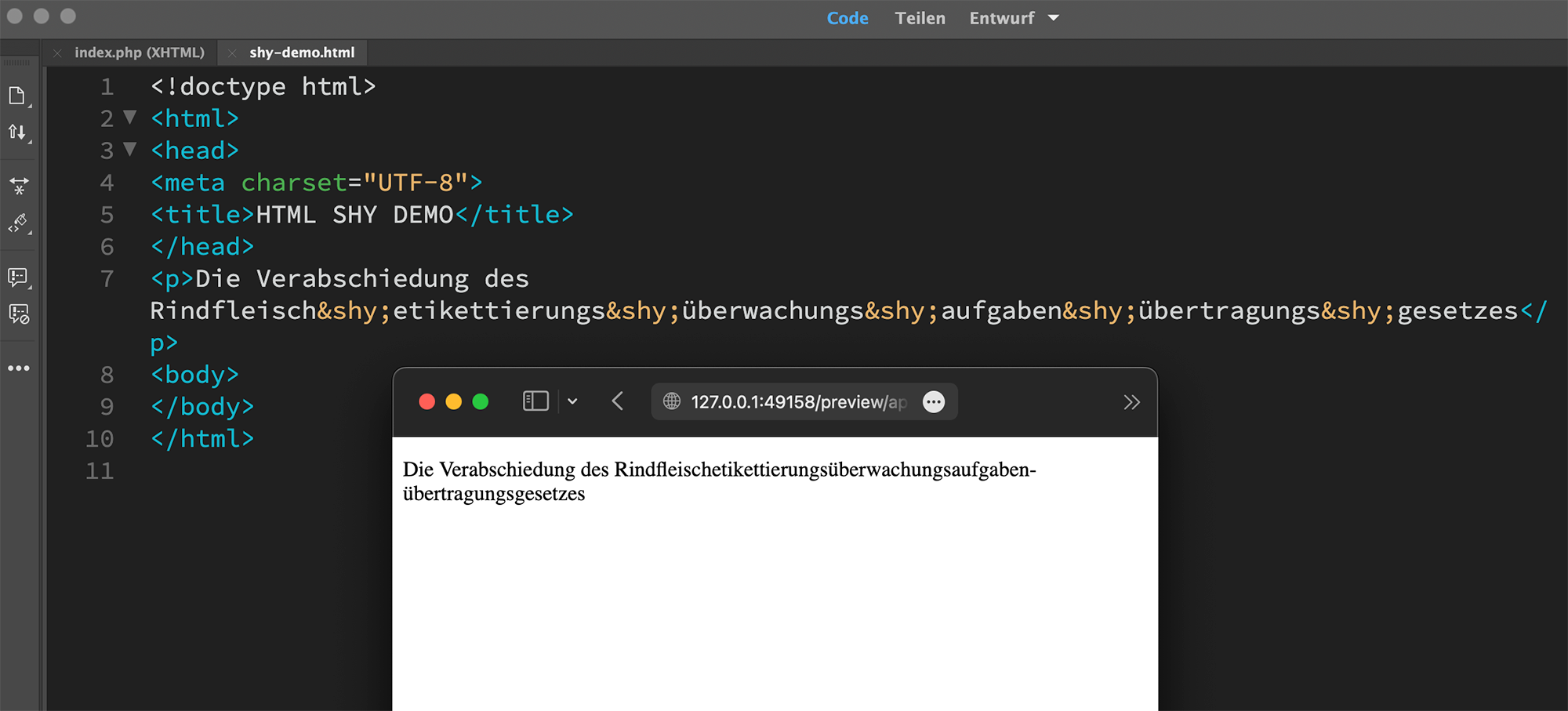
Auch lange und komplizierte Wörter werden sinnvoll getrennt, wenn man sich die Mühe macht, Trennfugen unsichtbar vorzuschlagen.
Der Bindehemmer
Mit dem Bindehemmer (U+200C) lassen sich Verbindungen von Zeichenfolgen direkt auf der Kodierungsebene unterdrücken und damit fest im Text verankern. Eine lokale Formatierung in einem Anwendungsprogramm ist damit nicht mehr nötig. Das Zeichen ist in verbundenen Schriftsystemen wie dem Arabischen besonders wichtig, lässt sich aber auch in der mikrotypografischen Anwendung lateinischer Texte sinnvoll nutzen. Die typische Anwendung ist hier die Unterdrückung von OpenType-Ligaturen, wenn sie in konkreten Wörtern die Lesbarkeit erschweren.
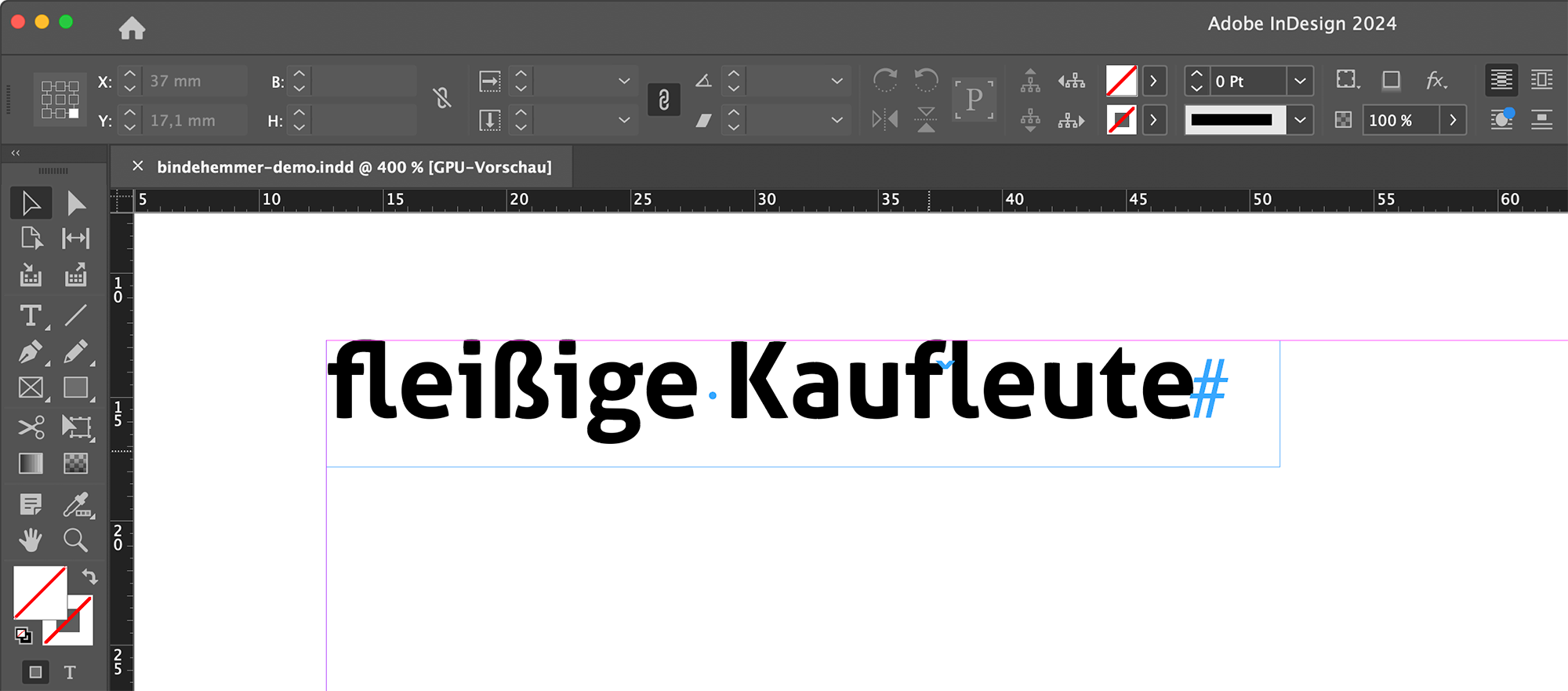
Während die automatisch aktivierte fl-Ligatur in »fleißige« sinnvoll ist, sollte sie in »Kaufleute« besser nicht über die Morphemgrenze hinweg gesetzt werden. Der Bindehemmer erlaubt diese ohne eine manuelle Formatierung der Textstelle.
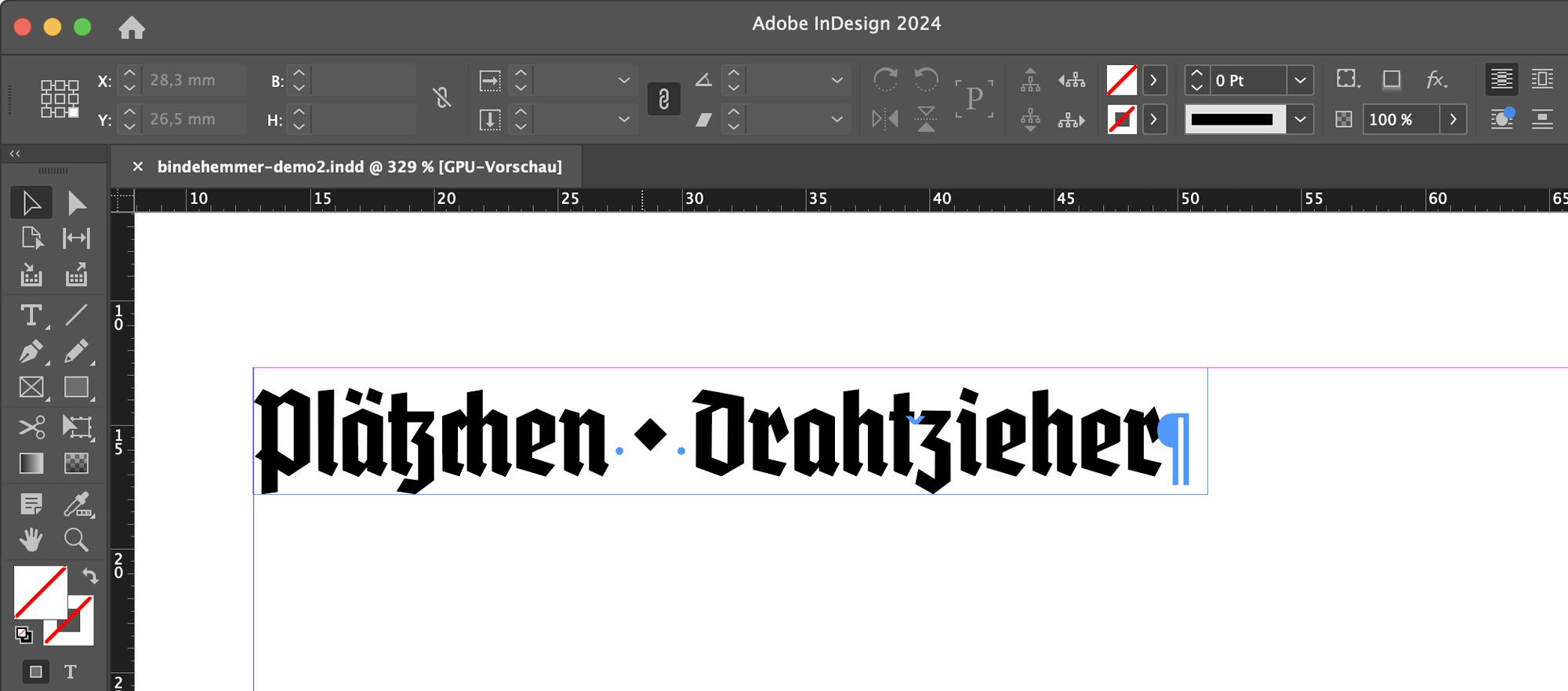
Fraktursatz-Ligaturen (wie hier das tz in Drahtzieher) verlangen ebenfalls regelmäßig einen Eingriff durch den Bindehemmer.
Eingabe:
Windows (in einigen Programmen):
Alt + 8204 (mit den Ziffern auf dem Ziffernblock)
2, 0, 0, C, Alt+C oder 2, 0, 0, C, Alt+X (in Microsoft-Office-Programmen)
MacOS: nicht direkt ansprechbar (Alternativen siehe hier)
E1-Tastatur: Extra-Wahltaste + m
HTML: ‌
Der breitenlose Verbinder
Der breitenlose Verbinder (U+200D) bildet das Gegenstück zum Bindehemmer. Hier wird eine Verbindung der umliegenden Schriftzeichen ausdrücklich vorgegeben. Anwender von Emojis nutzen das Zeichen regelmäßig, meist ohne dass es ihnen bewusst wäre. Denn ein Großteil der heute benutzbaren Emoji-Zeichen sind nicht einzeln im Unicode-Standard erfasst. Stattdessen werden sie als eine Zeichenkette aus mehreren Emojis kodiert. Das anzeigende Programm muss dann natürlich wissen, ob die betreffenden Emojis einzeln oder als ein kombiniertes Symbol angezeigt werden sollen. Und genau dies erfolgt durch das Einfügen des breitenlosen Verbinders zwischen die betreffenden Zeichen.
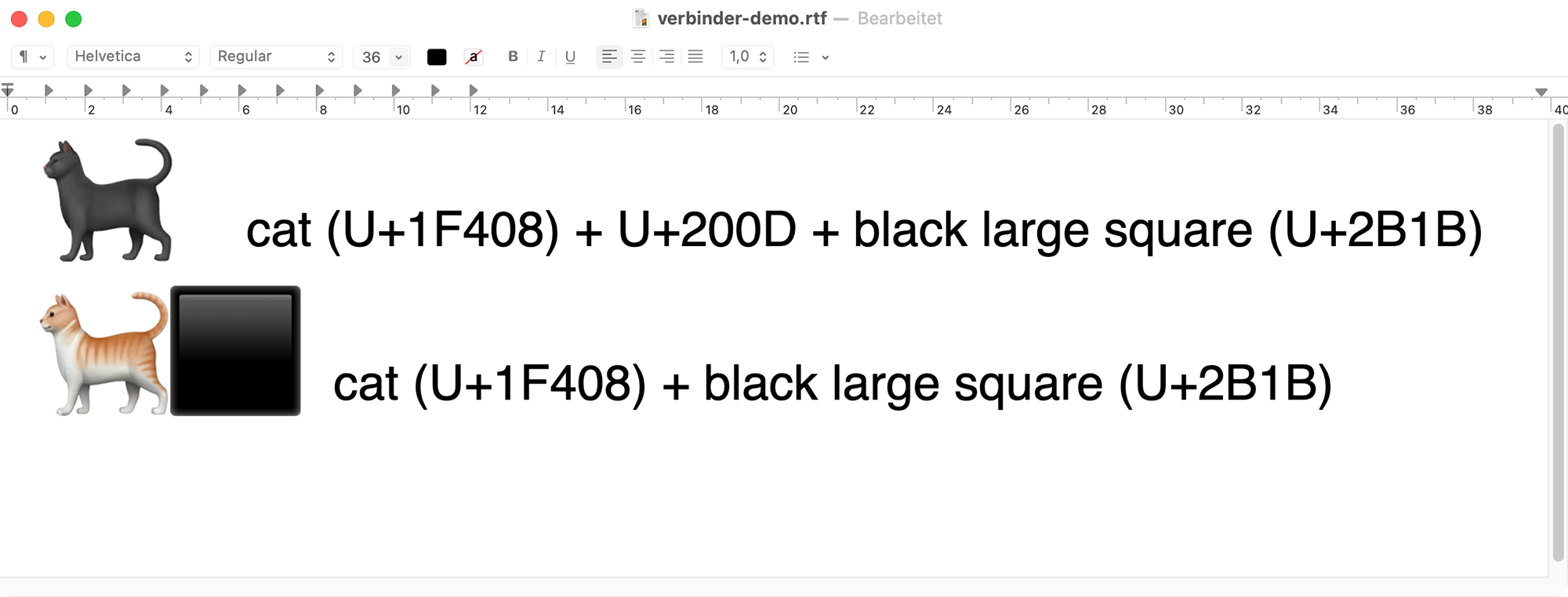
Die manuelle Eingabe solcher Sequenzen ist zwar selten nötig, es ist jedoch für Anwender dennoch nützlich, die Funktionsweise solcher Sequenzen zu kennen. Denn kommt es beim Kopieren entsprechender Sequenzen oder in bestimmten Programmen zu Problemen, erklärt sich so zumindest die Ursache.
Eingabe:
Windows (in einigen Programmen):
Alt + 8205 (mit den Ziffern auf dem Ziffernblock)
2, 0, 0, D, Alt+C oder 2, 0, 0, D, Alt+X (in Microsoft-Office-Programmen)
MacOS: nicht direkt ansprechbar (Alternativen siehe hier)
E1-Tastatur: Querstrichakzent (Alt[Gr] + ä) + Ö
HTML: ‍
Fazit
Mit den oben erklärten Zeichen lassen sich sinnvolle, mikrotypografische Optimierungen allein auf Kodierungsebene bewerkstelligen und sind damit nicht von den proprietären Funktionen konkreter Anwendungsprogramme abhängig. Im Idealfall wäre das entsprechende Tastaturkürzel dann zum Beispiel gleichsam im eigenen Browser, E-Mail-Programm, Textverarbeitungsprogramm, Layoutprogramm usw. nutzbar. Das Erlernen der Eingabe lohnt sich dann durchaus.
Allein die E1-Tastaturbelegung nach DIN 2137 bietet für alle genannten Zeichen ein direktes Tastaturkürzel an. Die erste Hardware-Umsetzung wurde 2024 unter dem Namen TypoTasten veröffentlicht.